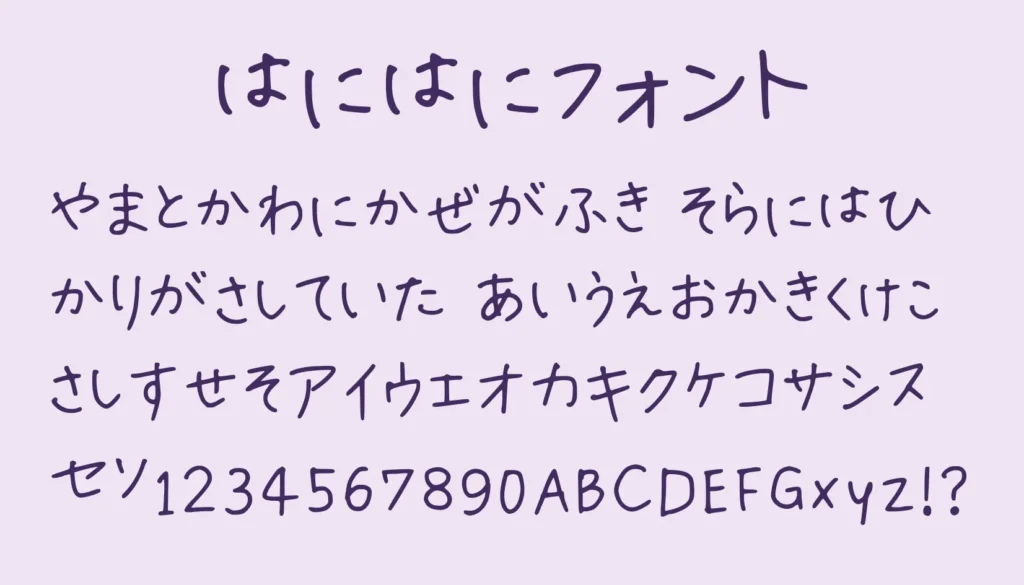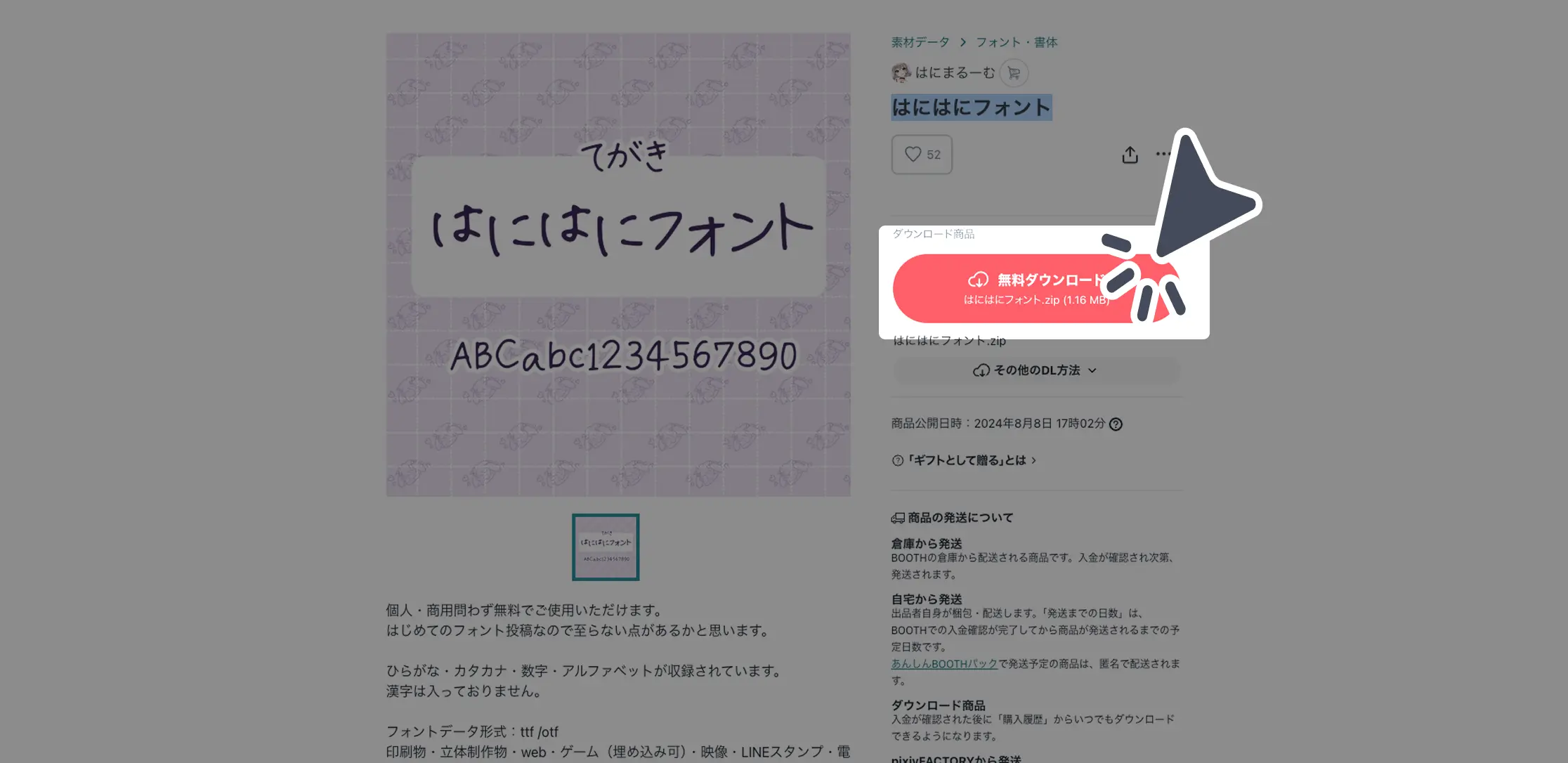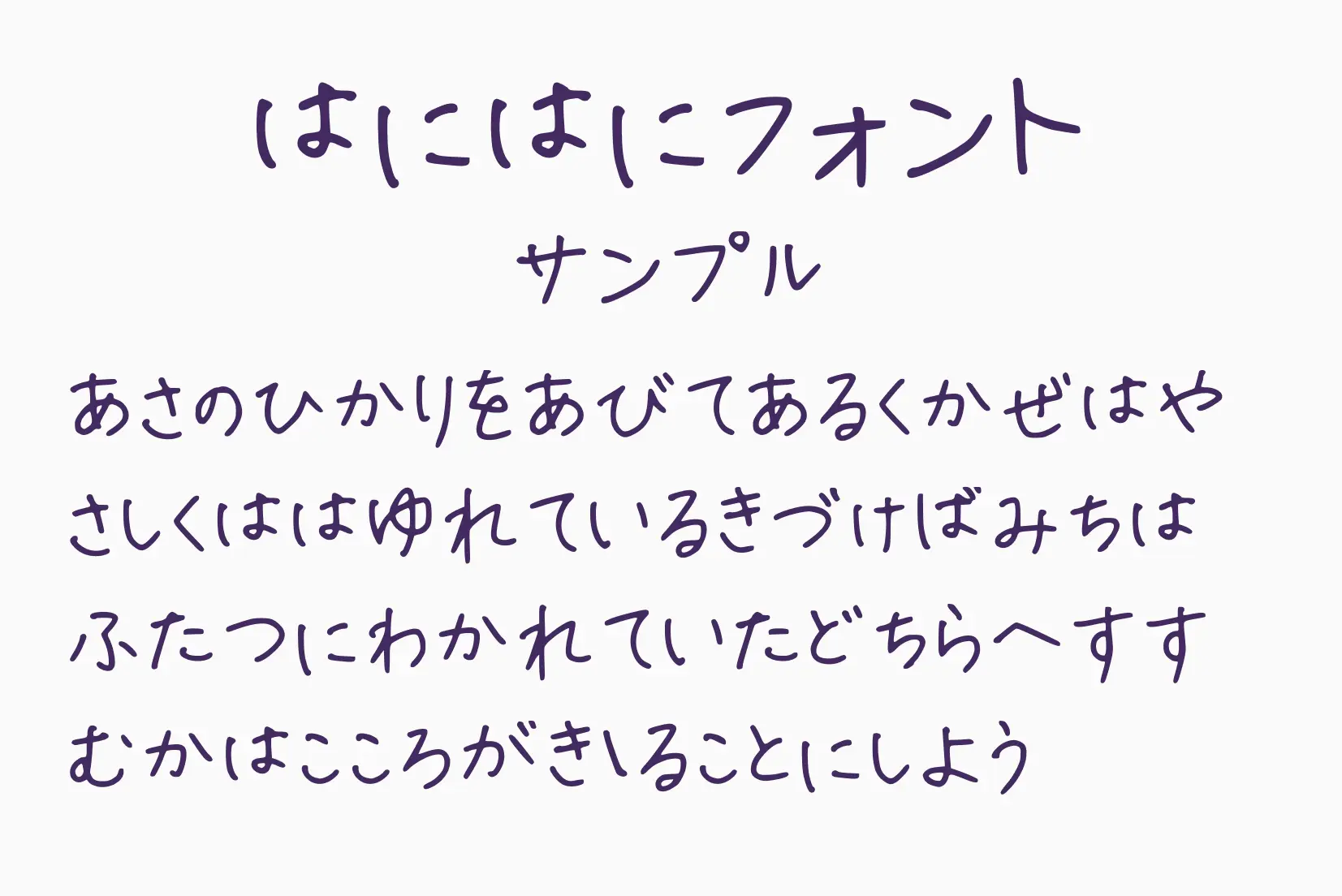
やわらかく丸みのある線が特徴の、ナチュラルで親しみやすい手書きフォント。適度に力の抜けたラフさがありながら、可読性も高く、日常的なデザインからポップな表現まで幅広く使いやすいのが魅力です。やさしい雰囲気を演出できるため、SNS投稿や動画テロップ、アイキャッチなどにも相性抜群。ひらがな・カタカナ・英数字に対応しており、シンプルながら温かみのあるデザインを求める人におすすめのフォントです。
はにはにフォント